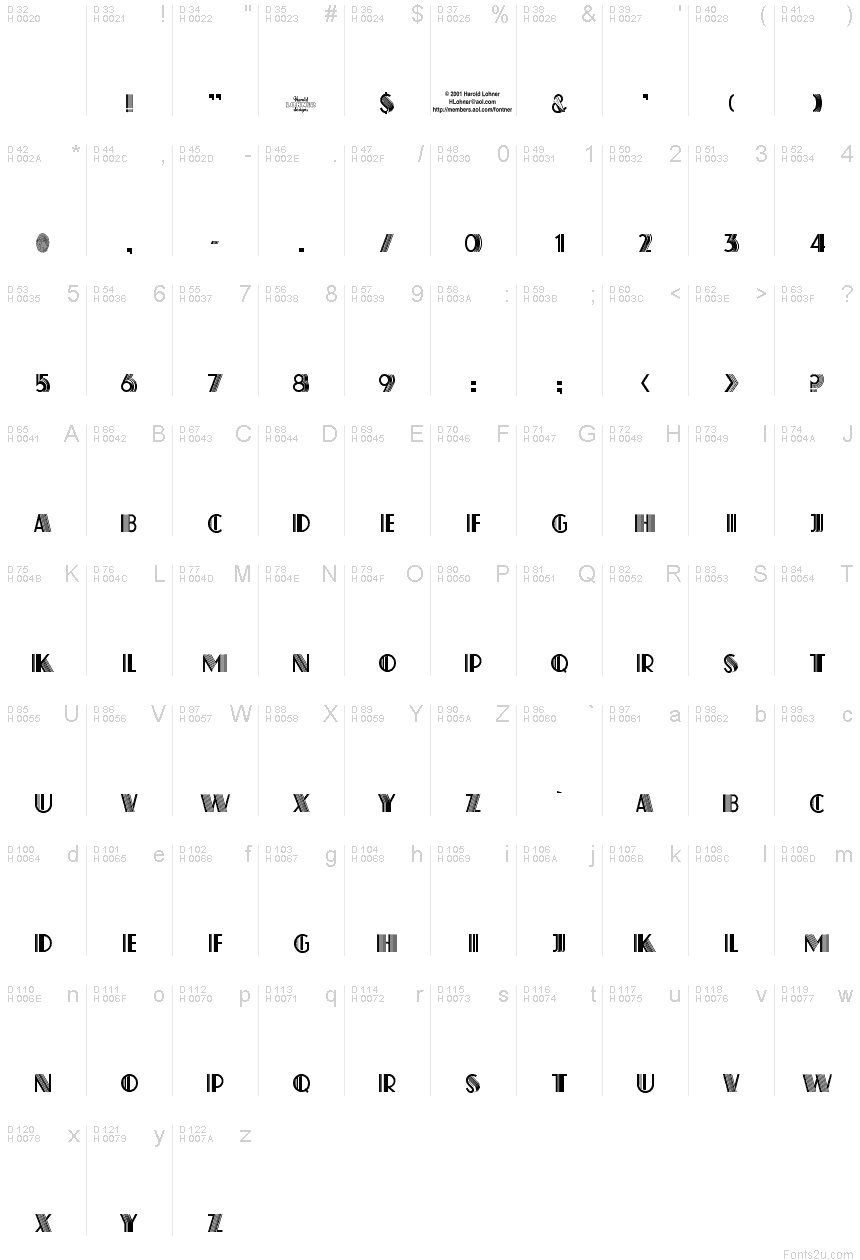
Atlas
Atlas od Harolda Lohnera to darmowy, utrzymany w klimacie groovy font typu display. Każda litera przypomina stos gęsto ułożonych pionowych pasków – jak zamrożony w czasie pokaz świateł w stylu vintage. Pociągnięcia są odważne, a jednocześnie lekkie; czarno-białe pasy pulsują podczas czytania, nadając nagłówkom wrażenie ruchu i głębi bez dodatkowych efektów. To krój graficzny, rytmiczny i niemożliwy do zignorowania.
Atlas sprawi, że Twoje tytuły nabiorą charakteru na plakatach w stylu retro, okładkach albumów, ulotkach, w brandingu, na opakowaniach czy w mediach społecznościowych. Ten darmowy font najlepiej prezentuje się w dużych rozmiarach, gdzie jego prążkowana tekstura naprawdę ożywa. Zestaw go z czystym, geometrycznym krojem bezszeryfowym w tekście głównym, aby nie przyćmić jego wyjątkowego rytmu.